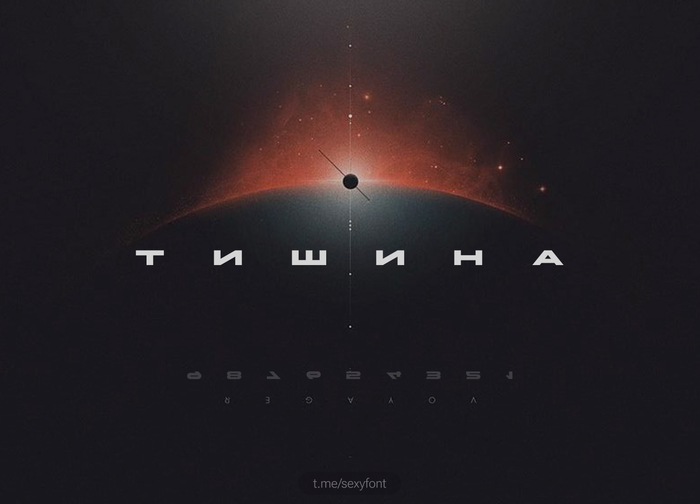
Шрифт Akony. Бесплатный. Кириллица
Akony. Не так часто встретишь хороший, размашистый шрифт. Подойдет для коротких заголовков. У меня как обычно ассоциации с космосом. В презентации показал. Но в целом зайдет и под бизнес и под ИТ, авто и т.п